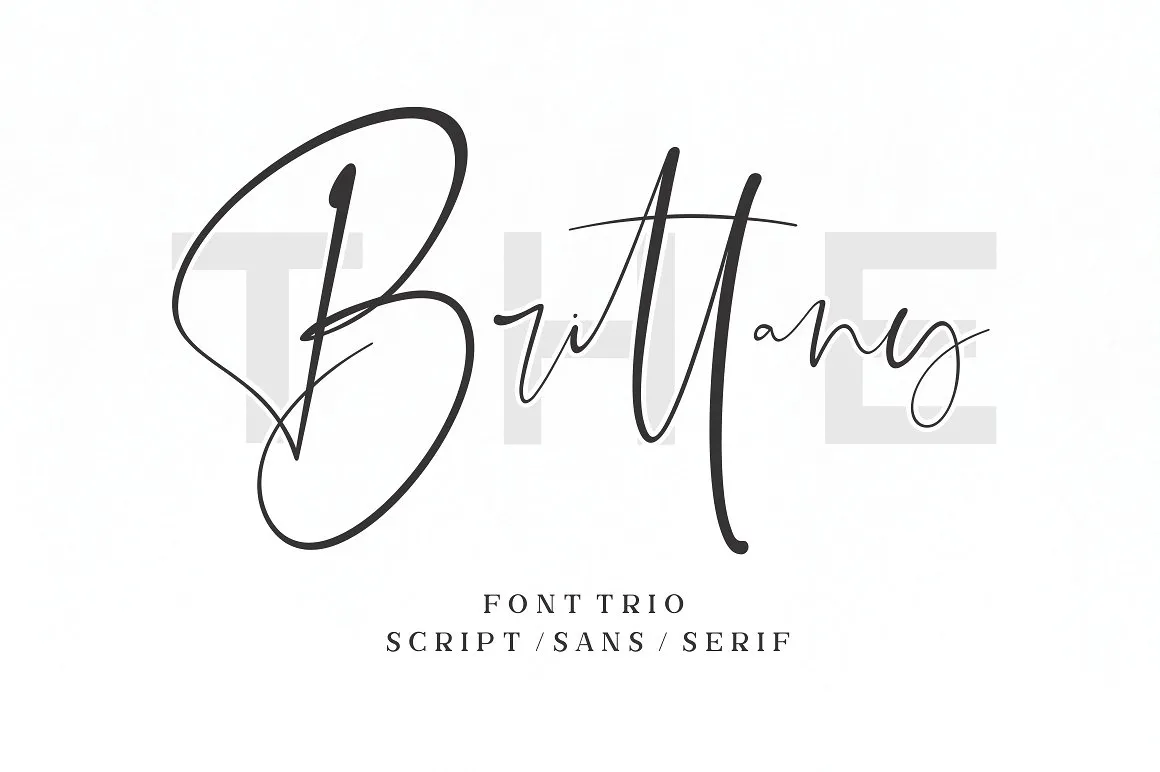
The Brittany Font Trio – Download Grátis
Seja uma fonte versátil para projetos variados, a Brittany Font Trio oferece três estilos distintivos – script, serif e sans-serif – perfeitamente conjugáveis para criar designs modernos e elegantes. Esta família de fontes foi criada por Sronstudio, com um design refinado que destaca-se em qualquer projeto. Com cinco estilos disponíveis para combinações perfeitas, a Brittany permite-lhe explorar uma gama infinita de possibilidades gráficas. Seja você designer de fotos que deseja criar logotipos ou assinaturas com água-marinha, criador de conteúdo de quotes e capas de álbuns, ou mesmo um profissional das cartões de visita da sua empresa – a Brittany é a escolha certa. Não hesite em explorar as várias maneiras pelas quais esta font pode contribuir para o seu próximo design.